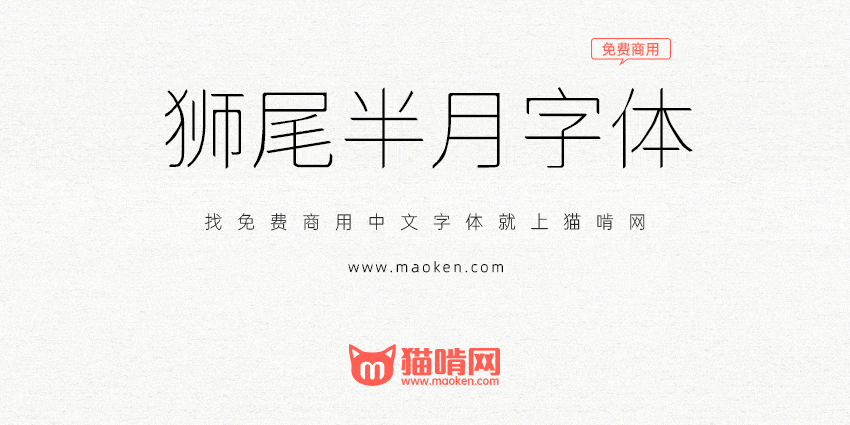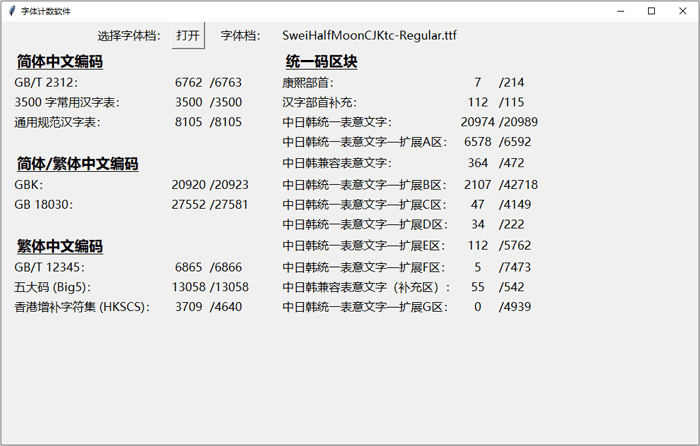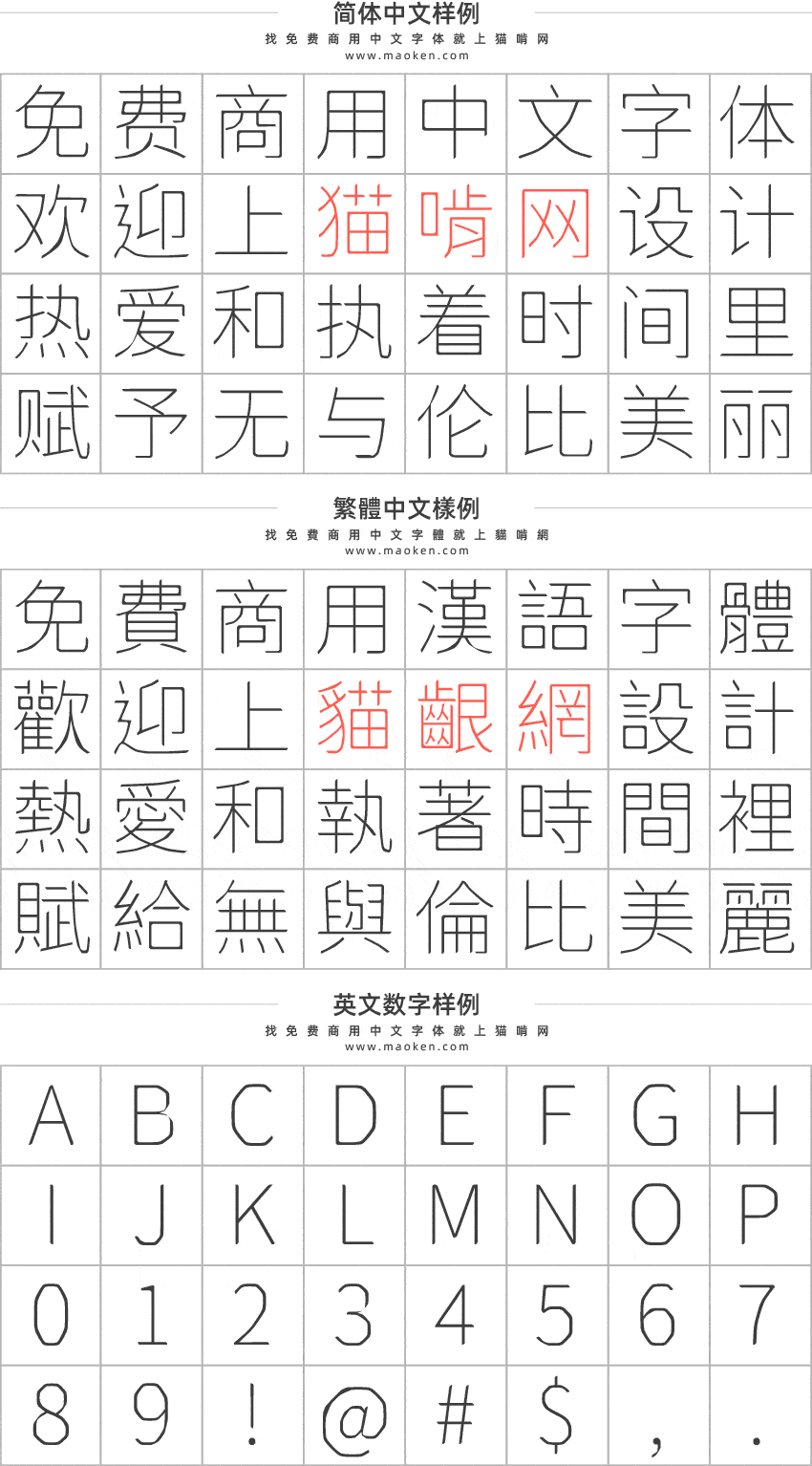
人生很多事情的发生都是一场意外。Max本来想挑战看看把思源黑体变成圆体的,在修改字型档案的过程中,Max的程式没写好,就意外地遇到一个半月形状的笔触,觉得也长的也满有趣的,就顺手上传给大家用看看。
狮尾半月字体基于思源黑体的拔脚和加半圆改造,不圆也不方的字体,特色之一是“十”长的像忍者的手里剑。狮尾半月字体和思源黑体支持简体中文、繁体中文、韩文与日文,而且具有7个字重。
1、这不是一个专业的字体,完全是使用程序改造而成的。
2、很多字还是可以看到思源黑体的的直角。
3、由于Max对字体编码方式完全不清楚,相较于原版的思源黑体,可能有掉一些符号或不常用的字。
5、演算黑科技将字体变半圆,请参考 /python/ 目录下的脚本档案。透过调整程式码,也许也可以产生出新的有趣字型。目前的程式应该还有很多错误或需要再加强的地方。
ver 2.061(2020/06/25)
- Regular 的字重有调整了部份的常用字,因为拔脚之后,不平衡的问题。
ver 2.054(2020/06/15)
- 使用 Noto Sans v2.001,针对辶部及注音符号重新设计。
ver 1.045(2020/06/05)
- 拔掉「闢」的小脚。
- 简化「禺」「禹」系列写法。
- 调整转换字体的规则。
ver 1.041(2020/06/04)
- 拔掉中/甲/串系列的小脚。
ver 1.040(2020/06/01)
- 解决有些脚被误拔,例如:遐霞霵劘奜。
ver 1.030(2020/05/21)
- 拔掉「隹」部左下角的小脚。
ver 1.028(2020/05/21)
- 修正baseline inconsistant(拔脚后悬空)问题。
ver 1.016(2020/04/13)
- 修正异体字问题,使用aalt lookup
- 使用 TrueType Font
- 增加常用异体字的支援。(manually ‘aalt’ lookup)
ver 1.013(2020/04/12)
- 调整风格。
ver 1.012(2020/04/11)
- 增加为四种字重:Demi-Light,Light,Regular,Regular。
- 增加常用异体字的支援。(manually ‘aalt’ lookup)
ver 1.010(2020/04/08)
- 调整风格,并增加 Medium 的字重。
- 修正「馋」系列的勾的笔画。
ver 1.008(2020/04/08)
- 狮尾半月字体发布第一版。